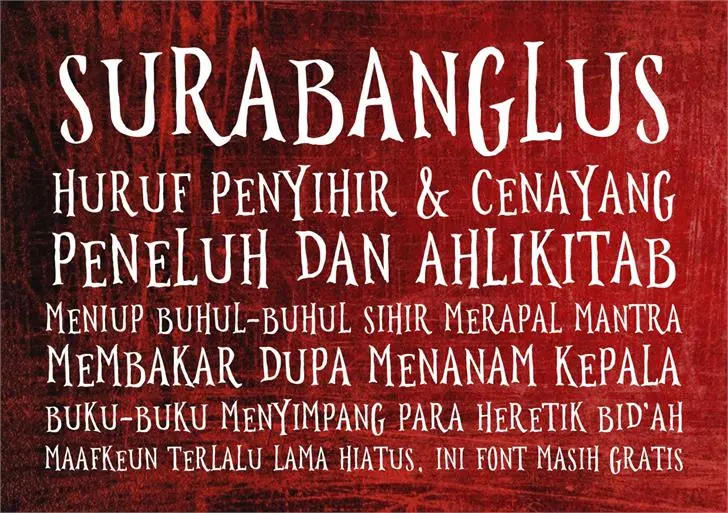
A fonte ‘Surabanglus’ é uma elegante escolha para qualquer projeto que exige um toque sofisticado e profundo. Inspirada no título do conto “Kecanduan Senyum” de Ahmad Tohari, parte do livro “Senyuman Karya-Min”, essa fonte serifa traz consigo uma textura intrigante que flui naturalmente nas letras. Seu nome é uma referência a um tipo específico de pimenta amarga conhecida no sudeste asiático, sugestivamente representando sua natureza poderosa e instintiva. Inspirada nos contos de Ahmad Tohari, Surabanglus oferece um lembrete de que mesmo as coisas mais simples podem carregar uma carga complexa e intrigante. Um convite para explorar os mundos sutis entre palavras e escrita, surabanglus é a escolha perfeita para qualquer projeto que valoriza detalhes e profundidade.